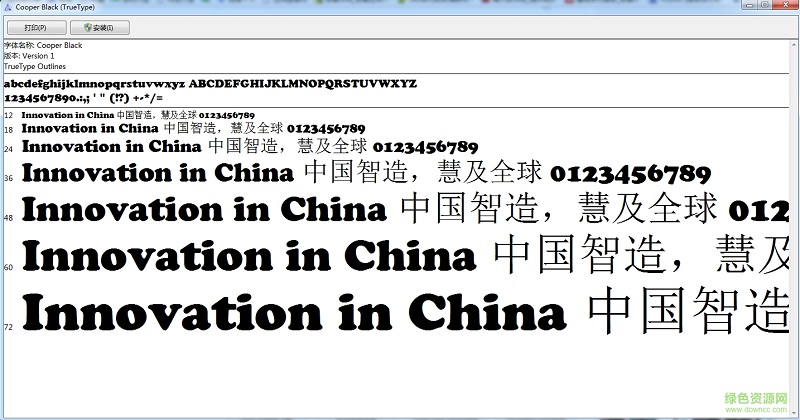
cooperblack字體
cooper black字體是一款漂亮圓潤的英文字體,該字體線條較粗,氣勢雄健,可用于藝術(shù)設(shè)計領(lǐng)域或是廣告字體,喜歡這款字體的小伙伴趕緊來綠色資源網(wǎng)下載吧!
cooper black特點
字型圓潤飽滿,新穎活潑,粗而不重,胖而不臃,給人以生機盎然的感受。適用于書、報、雜志和各類印刷品的標題及裝飾用字。